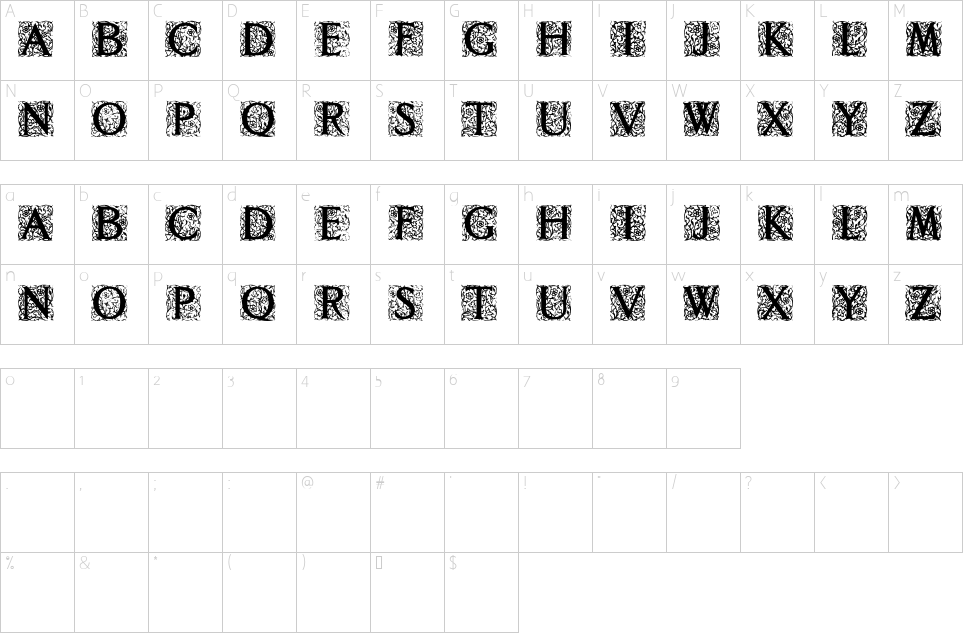
Decorated Roman Initials Font – Download Grátis
A fonte Decorated Roman Initials é uma escolha ideal para aqueles que desejam adicionar um toque único a seus designs digitais com elegância e profundidade. Desenhada pelo designer desconhecido Dieter Steffmann, esta font oferece inicializações decoradas em romano, que são perfeitas para introduzir um toque de sofisticação nos títulos e cabeçalhos de suas páginas ou projetos gráficos. O aspecto ornamental destas iniciais adiciona uma captação especial aos elementos-chave do seu design, tornando-a uma fonte popular entre designers e criativos digitais. Com seu download fácil para Windows e Mac, esta font pode ser integrada em um grande número de ferramentas de edição gráfica sem restrições. É uma maneira fantástica de dar vida a seus projetos com um toque que destaca o estilo do design.